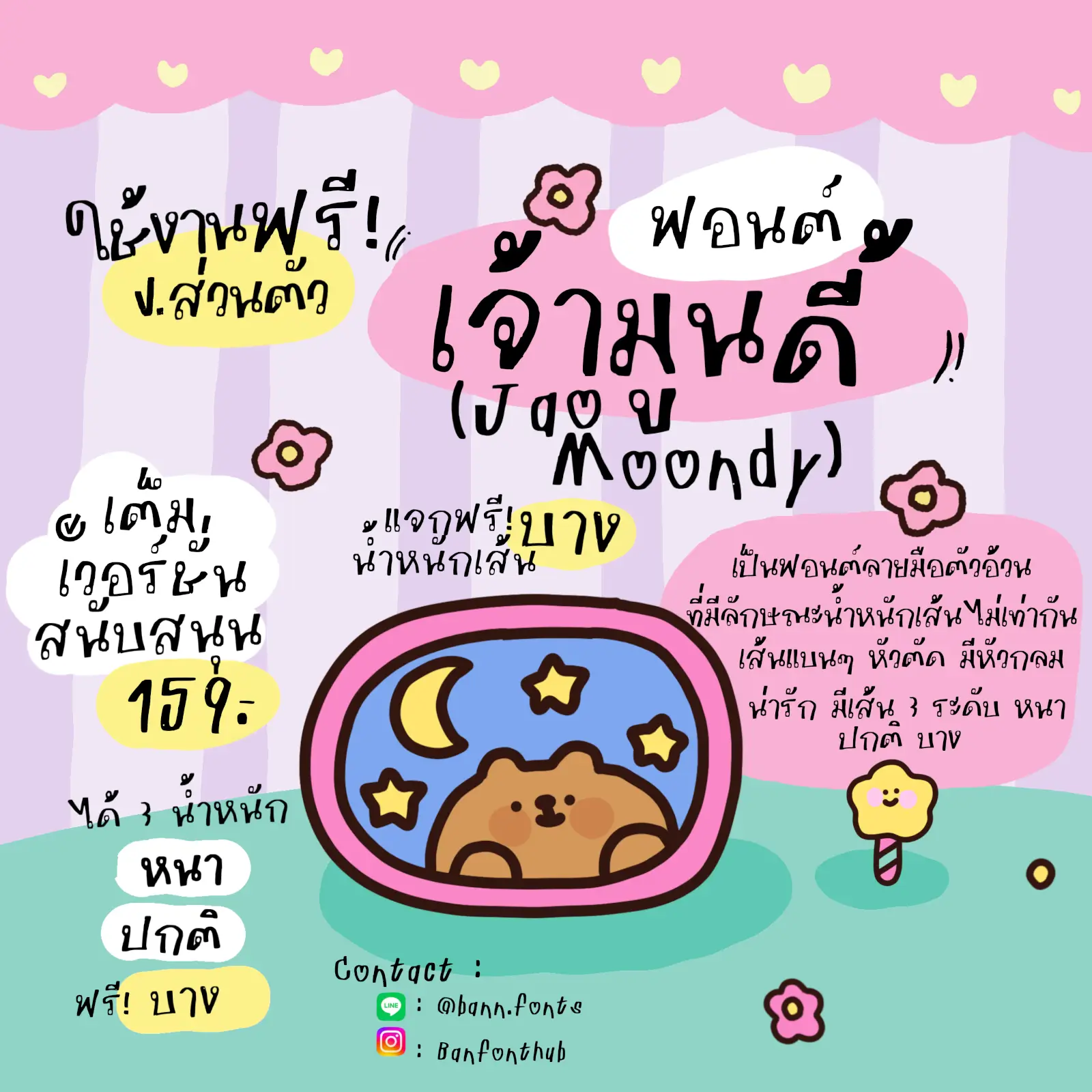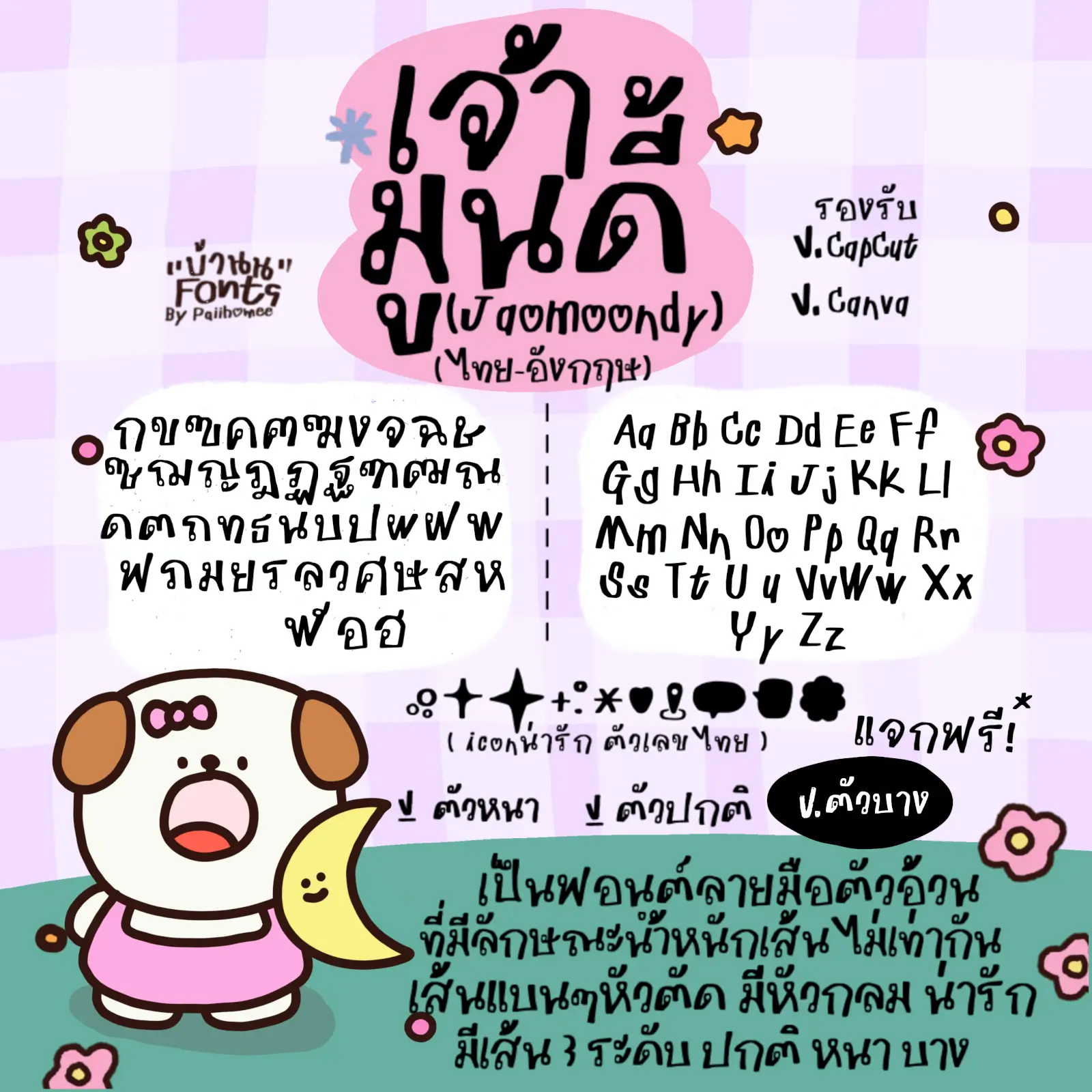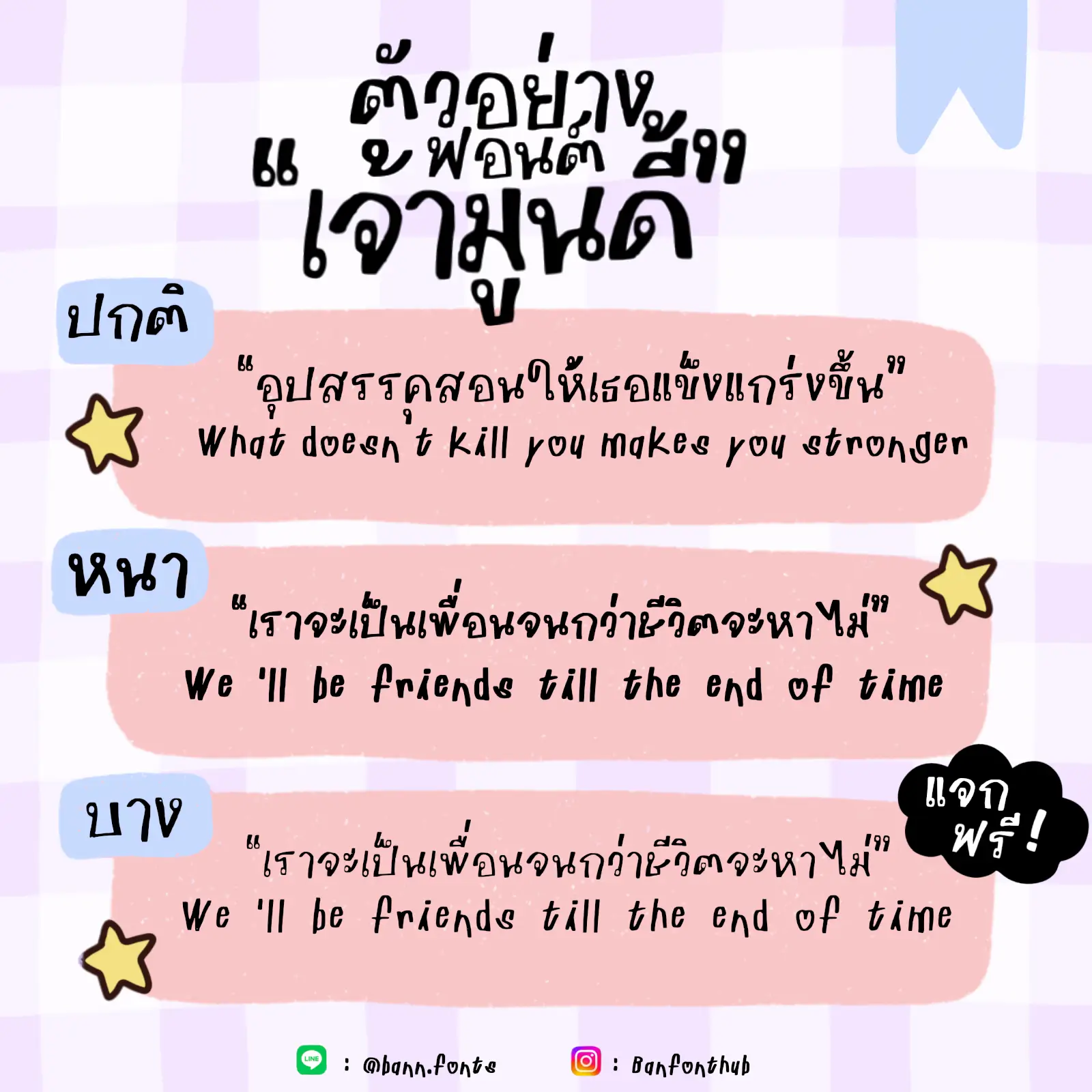
ฟอนต์เจ้ามูนดี้ ☕️ – ฉบับรุ่นตัวบางเท่านั้น! ใช้งานส่วนตัวได้ฟรี
แจกให้ใช้งานฟรี! สำหรับคนที่ชอบฟอนต์ลายมือ น่ารักๆ มีความเหลี่ยมๆ
✍🏻แนะนำว่า นำไปใช้งานกับการเขียนปกคลิป ปกรูป สรุปงาน จดโน้ต จดบันทึก
แจกฟรี 1 สไตล์ (ตัวบาง)
หากสนใจใช้งานเต็มเวอร์ชัน 3 ขนาด (เส้นหนา เส้นบาง เส้นปกติ)
เจ้ามูนดี้ (JaoMoondy)